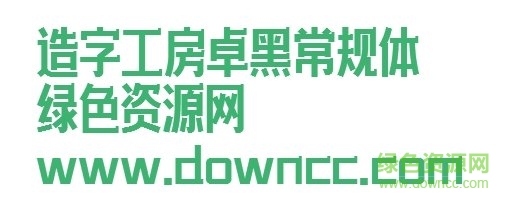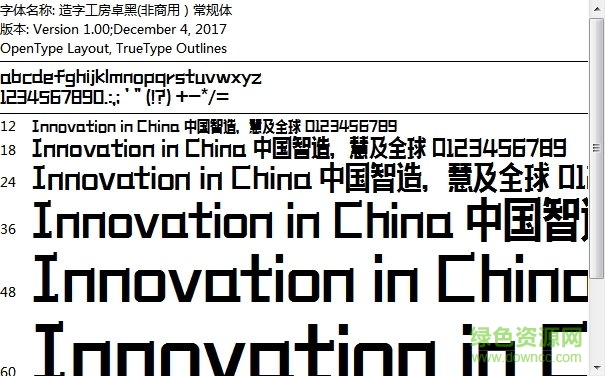
造字工房卓黑體是造字工房2017年推出的特色黑體字體,自帶加粗加黑設(shè)計,在每個字體的部分都多出一截,嚴(yán)肅中透著一股滑稽,喜歡的朋友就來綠色資源網(wǎng)試試吧!
造字工房卓黑體,字形瘦長,筆畫平直,其風(fēng)格雄強(qiáng)正肅,引人注目。字形結(jié)構(gòu)嚴(yán)謹(jǐn),實用性強(qiáng),橫畫上的方形凸起處理,令字形個性鮮明,更顯凝練正則之勢。適用于大標(biāo)題及個性品牌設(shè)計推廣等環(huán)境。